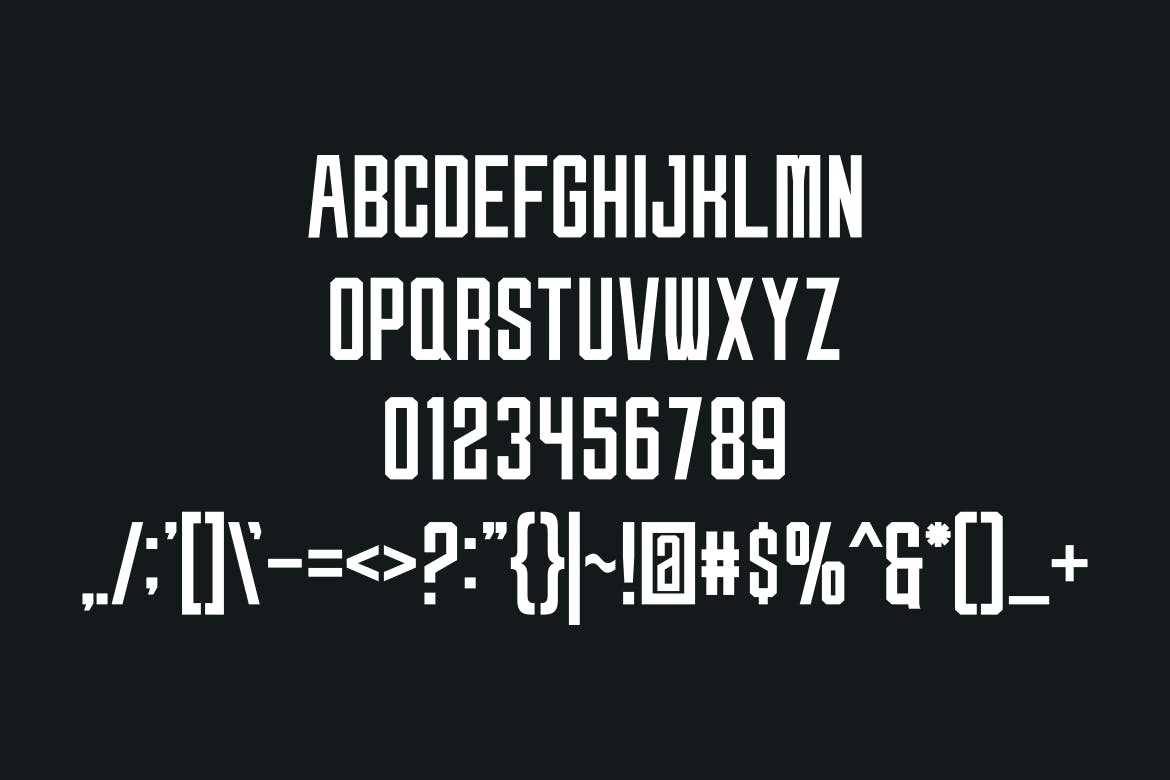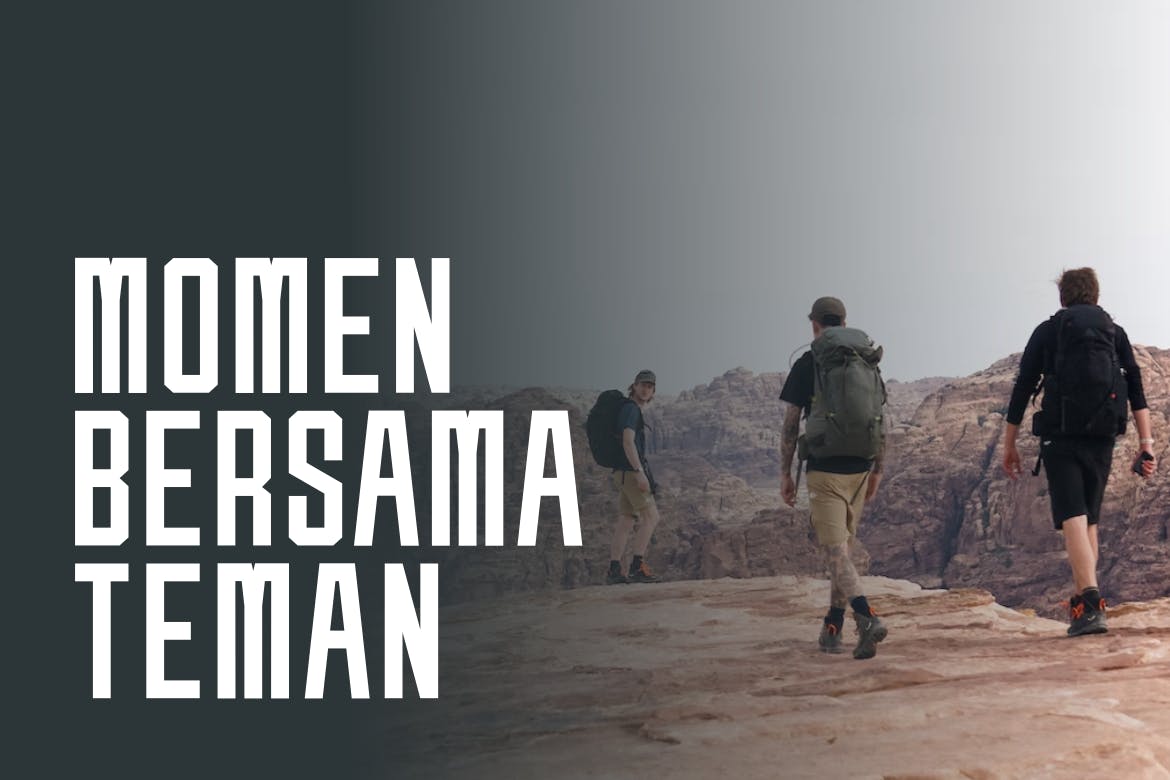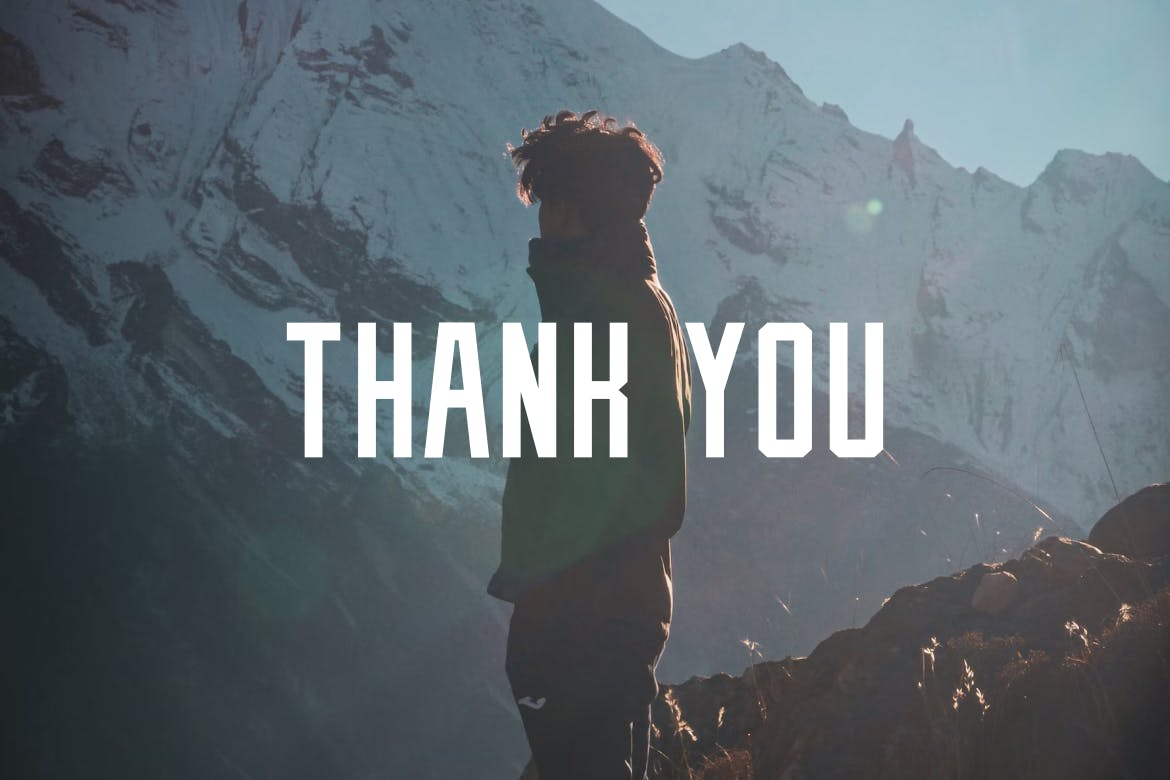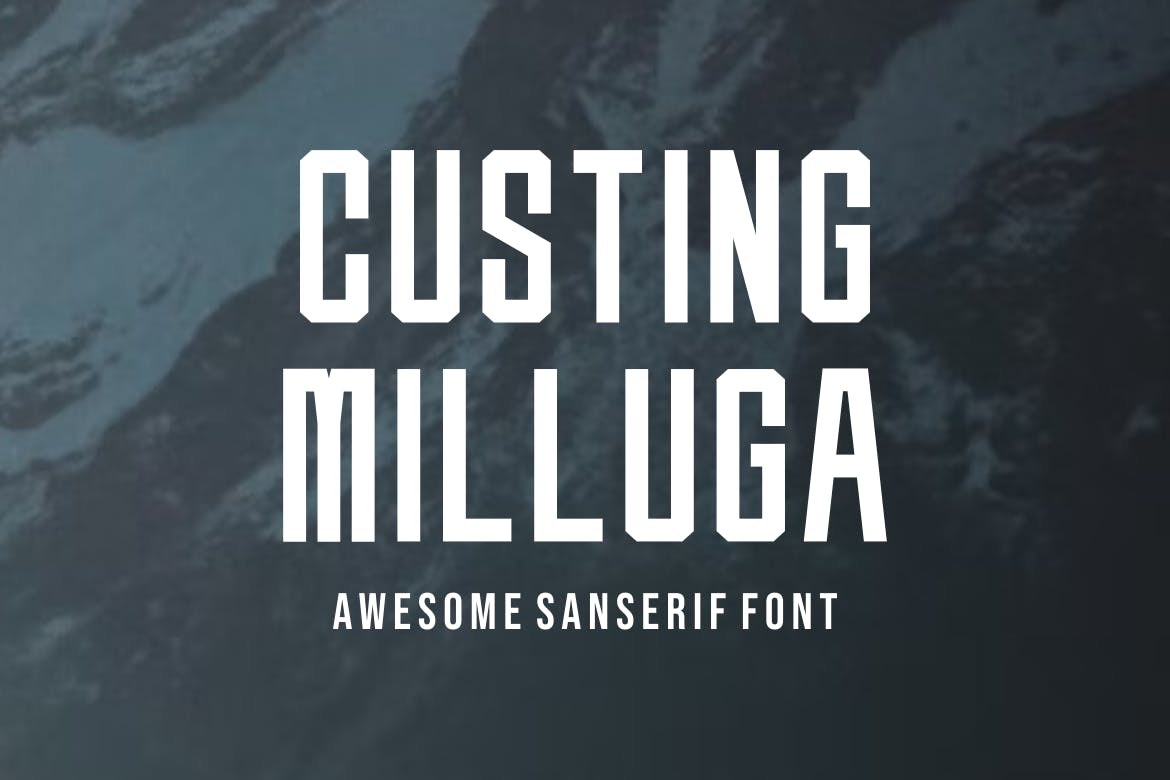
CustingMilluga Modern Font
معرفی محصول جدید ما CustingMilluga - فونت مدرن
CustingMilluga - فونت مدرن یک فونت نمایشی جسور و اصیل است. این فونت برای هر پروژه برندینگ مانند لوگو، چاپ تیشرت، ورزش‌های الکترونیکی و بسیاری دیگر مناسب است و در انواع زمینه‌ها به خوبی جلوه می‌کند.
ویژگی‌ها
• حروف بزرگ